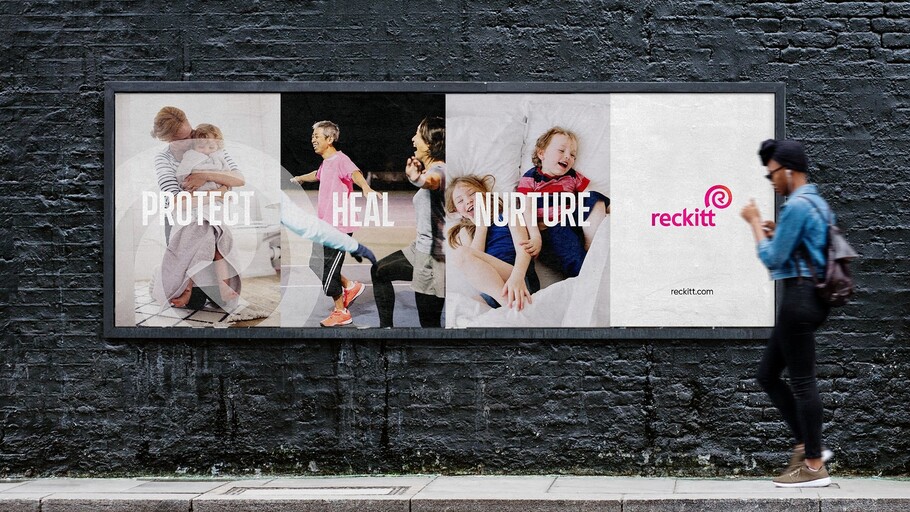
Die Rolle der Schrift beim Marken-Relaunch von Reckitt.
„ Die neue, maßgeschneiderte Schrift ‚Energy‘ ist unverwechselbar, zugänglich und passt genau zur Reckitt Benckiser Group. Sie erlaubt dem Hersteller, seine Botschaften selbstbewusst zu kommunizieren und sein Engagement für einen positiven Wandel glaubhaft zu verankern. “
Conran Design Group
Nachdem die Reckitt Benckiser Gruppe ihre Strategie für ein nachhaltiges Wachstum definiert und bekannt gegeben hatte, wollte das Unternehmen seine Transformation auch durch eine Neugestaltung und den Relaunch der Marke unter dem neuen Namen „Reckitt“ zum Ausdruck bringen. Alle Verbraucher sollte unmittelbar spüren, dass Reckitt aktiv auf einen sich schnell wandelnden Markt reagiert und als Unternehmensmarke eine verantwortungsvolle Rolle in der Gesellschaft übernimmt.
Schon in der Frühphase des neuen Markendesigns wurde Reckitt und der Conran Design Group der klare Vorteil bewusst, wenn man mit einer eigenen, individuellen Schrift in den Markt geht. Denn eine maßgeschneiderte Schrift verleiht der visuellen Identität einer Marke einen individuellen, glaubwürdigen Anstrich, mit dessen Hilfe sich die geänderte Markenpersönlichkeit schnell neu darstellen und verbreiten lässt. Wenn das ästhetisch und technisch richtig gemacht wird, kann eine solche Hausschrift nicht nur den Kern der Markenpersönlichkeit einfangen, sondern diesen auch  konsistent über alle Plattformen, Sprachen und Anwendungen hinweg transportieren.
Conran und das Monotype Studio waren sich von Anfang an im Klaren darüber, was sie mit dem Exklusivschrift-Projekt erreichen möchten. Vor allem Conran hatte eine genaue Vorstellung über die Kommunikationsziele der nahen Zukunft und was ein guter Custom-Font für den Auftraggeber leisten kann.
Erste Designkonzepte des Monotype Studio für eine Headline-Schrift zeigten allen Beteiligten, dass das Design der neuen Schrift einen starken Fokus auf Vielseitigkeit und Einfachheit haben muss, und dass diese Eigenschaften über alle Berührungspunkte hinweg mit der Marke zu transportieren sind. Friedrich Althausen, Schriftdesigner bei Monotype und Leiter des Projekts, drängte darauf, dass sowohl eine Displayschrift als auch eine Textfamilie zu entwickeln sei.
Es war eine Herausforderung, die schmale, sofort wiedererkennbare Display-Schrift mit einer gut lesbaren Textfamilie in Beziehung zu bringen. Der stetige Abgleich beider Designstile sorgte schließlich dafür, die markanten Eigenschaften der Reckitt-Schriftfamilie noch tiefer zu verwurzeln, und ihre Identität auf ein Maximum zu steigern.
„ Durch die Konzentration auf Grundformen wie Kreisbögen und Geraden und die Reduzierung von Details schöpft ‚Energy‘ ihre Kraft vor allem aus der Klarheit und den harmonischen Proportionen. Später wurde den Buchstaben Details hinzugefügt – feine Rundungen und schräge Abstriche –, die der Schrift mehr Charakter und einen höheren Wiedererkennungswert geben. “
Friedrich Althausen, Type Designer bei Monotype.
Mit der neuen, maßgeschneiderten Schrift wird die typografische Kommunikation von Reckitt sehr bald an Profil gewinnen. In einer Welt der digitalen Beschleunigung ist eine starke Schrift weit mehr als nur ein Markenbaustein: Sie selbst wird zur Botschafterin.